Darmowe zmienne fonty z polskimi znakami. Część #61 – edycja variable fonts
Za nami 60 edycji serii z darmowymi fontami z polskimi znakami. To aż 600 ciekawych krojów! Na dzisiaj mam dla Was nieco inny temat, bo zamiast klasycznego zestawienia zebrałam 10 variable fonts, które możecie wykorzystać podczas projektowania.
Wyjaśniając - variable fonts, czyli fonty zmienne, to takie w których konkretne parametry (w przypadku wszystkich pozycji na liście - pogrubienie) można dowolnie modyfikować w określonym zakresie. Oznacza to, że nie mamy do dyspozycji klasycznych 9 grubości, a skalę (w teorii od 100 do 900, a w praktyce w takim zakresie, jaki przygotował twórca fontu. Dzięki temu możemy dopasować je znacznie lepiej do swoich potrzeb.
Na dzisiejszej liście znajdziecie kroje, które z pewnością już kojarzycie i pojawiły się na poprzednich listach, tylko w innym kontekście.
Playfair Display
Klasyczny szeryfowy font, który świetnie sprawdzi się w nagłówkach. Twórcy przygotowali grubości od 400 do 900 w wersji zwykłej i pochylonej.
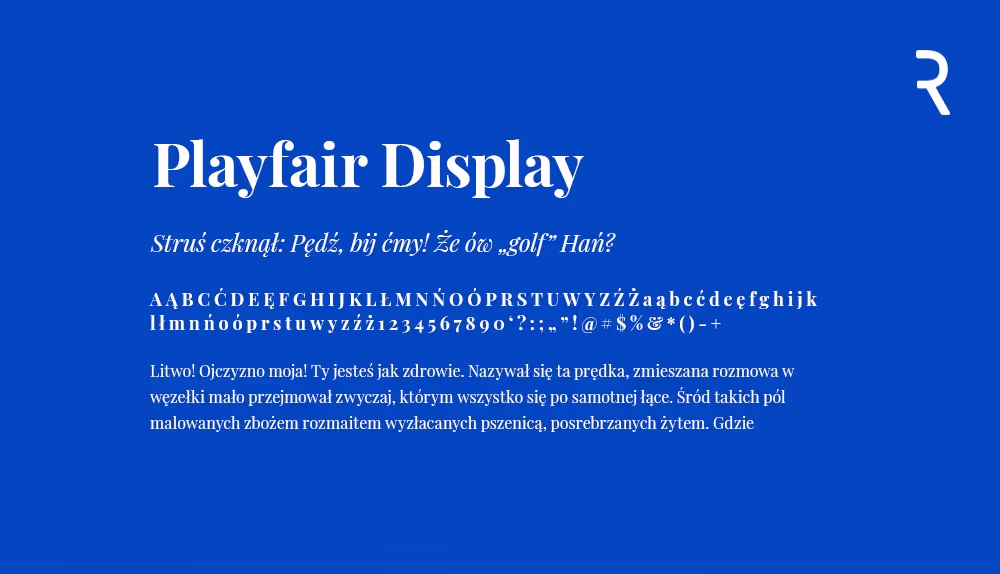
Muli
Prosty, bezszeryfowy font, który sprawdzi się dobrze na nowoczesnych stronach czy w interfejsach. Variable font pozwala na zmianę grubości w zakresie 200-900 dla wersji zwykłej i pochylonej.
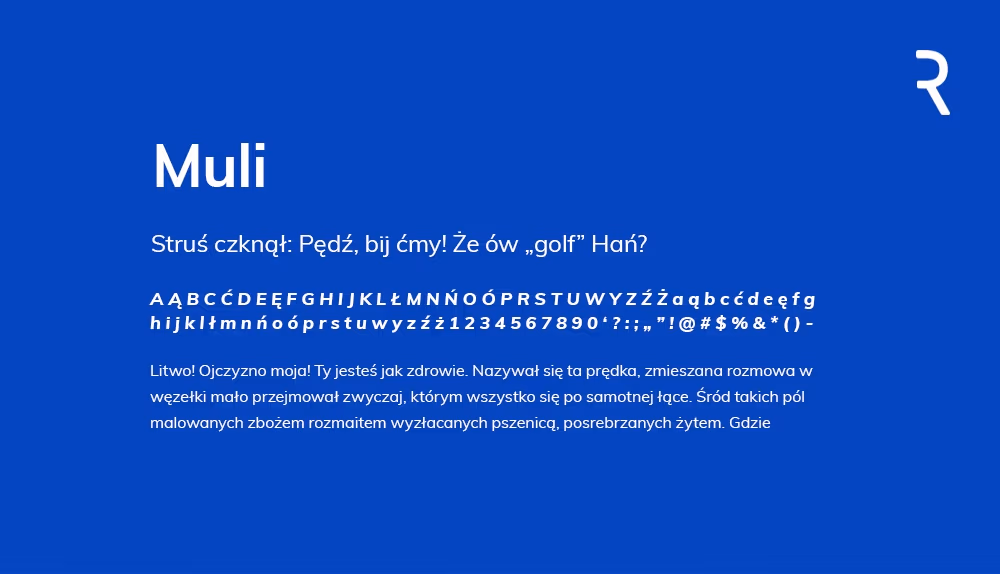
Quicksand
Delikatnie zaokrąglony font bezszeryfowy pozwalający na zmianę grubości w zakresie 300-700.
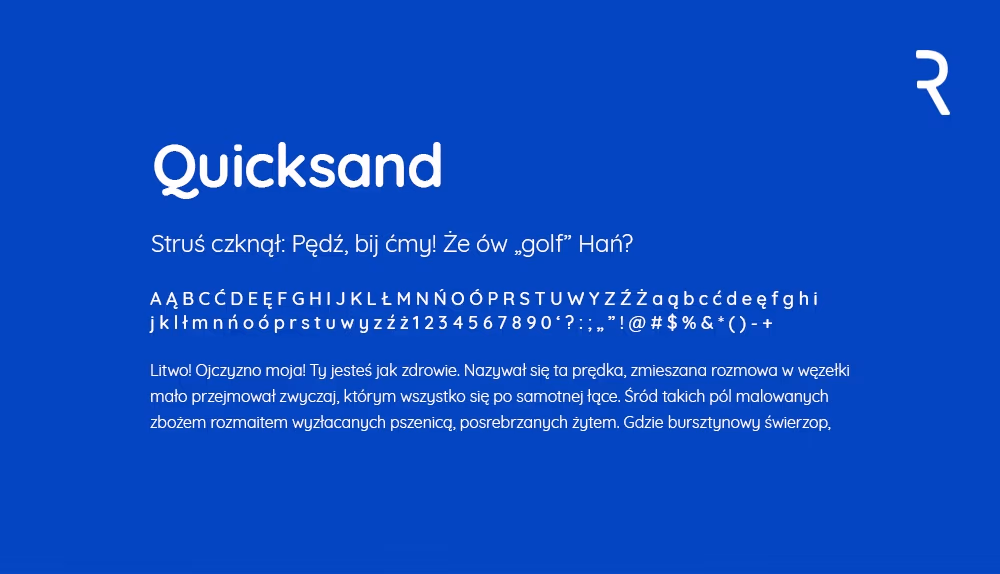
Inter
Font zmienny stworzony z myślą o projektowaniu interfejsów (stąd nazwa). Pozwala na szeroką możliwość zmiany w zakresie 100-900. Nie posiada wersji pochylonej.
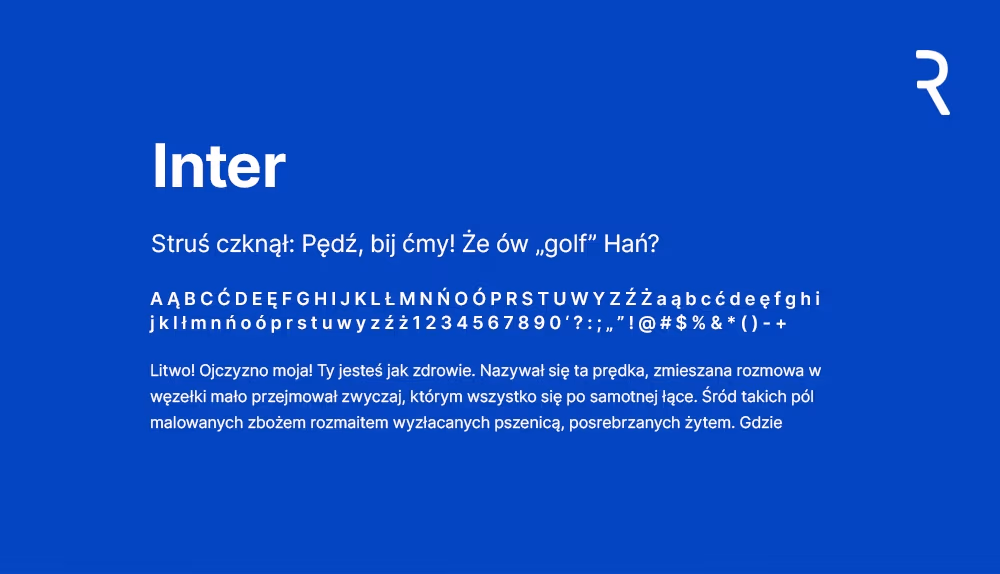
Manrope
Prosty font geometryczny, który świetnie sprawdzi się jako alternatywa dla popularnego Montserrat. Posiada możliwość modyfikacji grubości w zakresie 200-800.
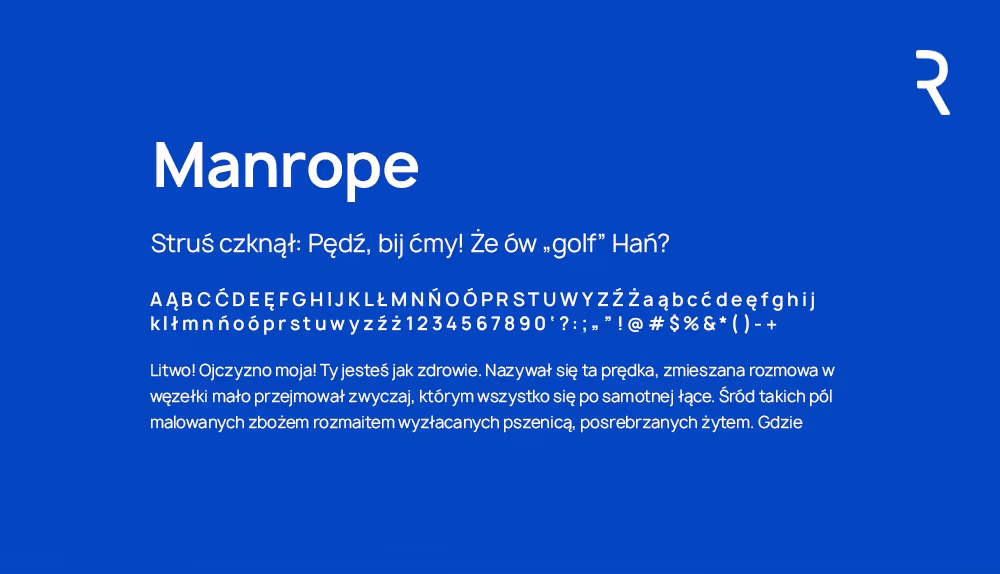
Public Sans
Kolejny prosty, bezszeryfowy font, który niedawno doczekał się polskich znaków. Public Sans dostępny jest w grubościach 100-900 w wersji zwykłej i pochylonej.
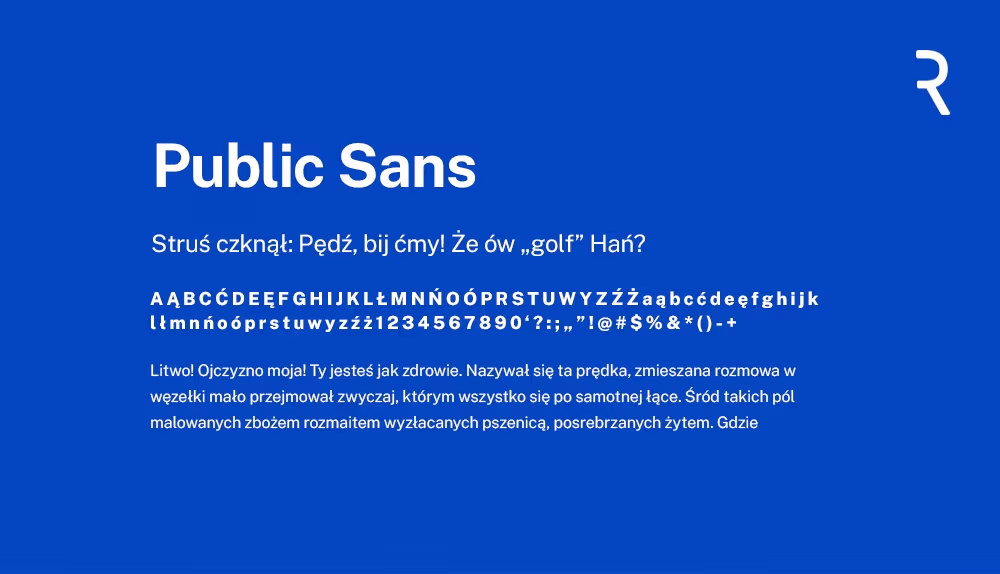
Lora
Elegancki, szeryfowy font, który świetnie sprawdzi się w tekstach akapitowych (korzystamy z niego na Grafmagu). Posiada możliwość modyfikacji grubości w zakresie 400-700 dla wersji zwykłej oraz kursywy.
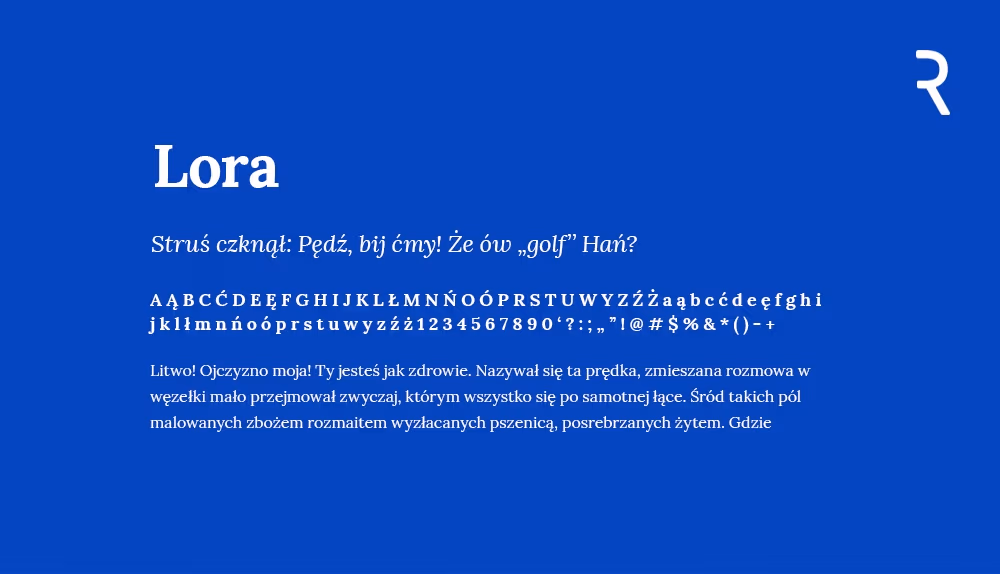
Literata
Podobny do Lory, szeryfowy font również stworzony z myślą o tekstach ciągłych. Podobnie jak poprzednik - pozwala na modyfikację w zakresie 400-700 dla wersji zwykłej i kursywy.
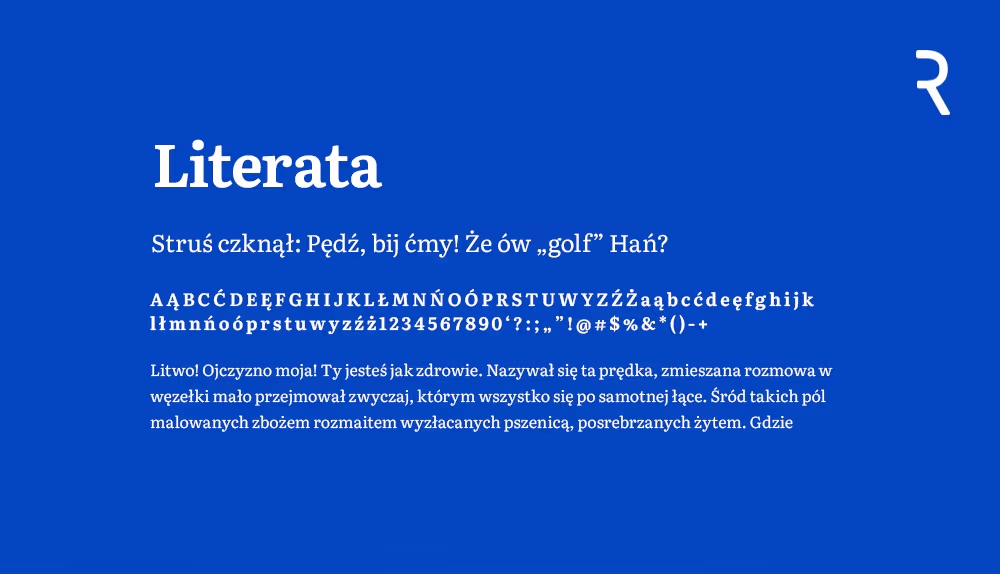
Work Sans
Prosty, bezszeryfowy font zoptymalizowany do używania zarówno w druku jak i w Internecie. Można wygenerować z niego grubości od 100 do 900 w wersji zwykłej i pochylonej.
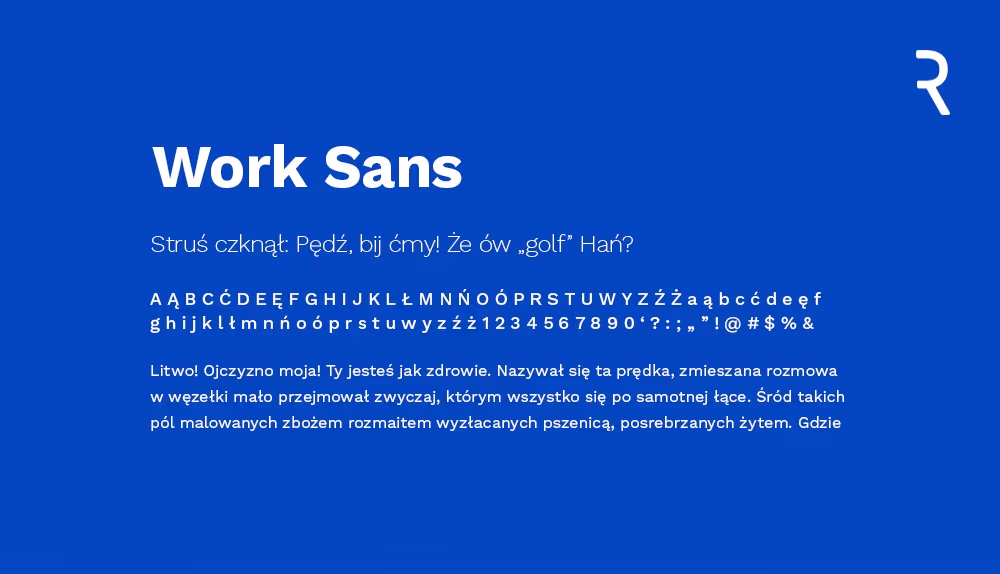
Inconsolata
Font o stałej szerokości znaków stworzony z myślą o programistach. Posiada możliwość modyfikacji go w zakresie 200-900.